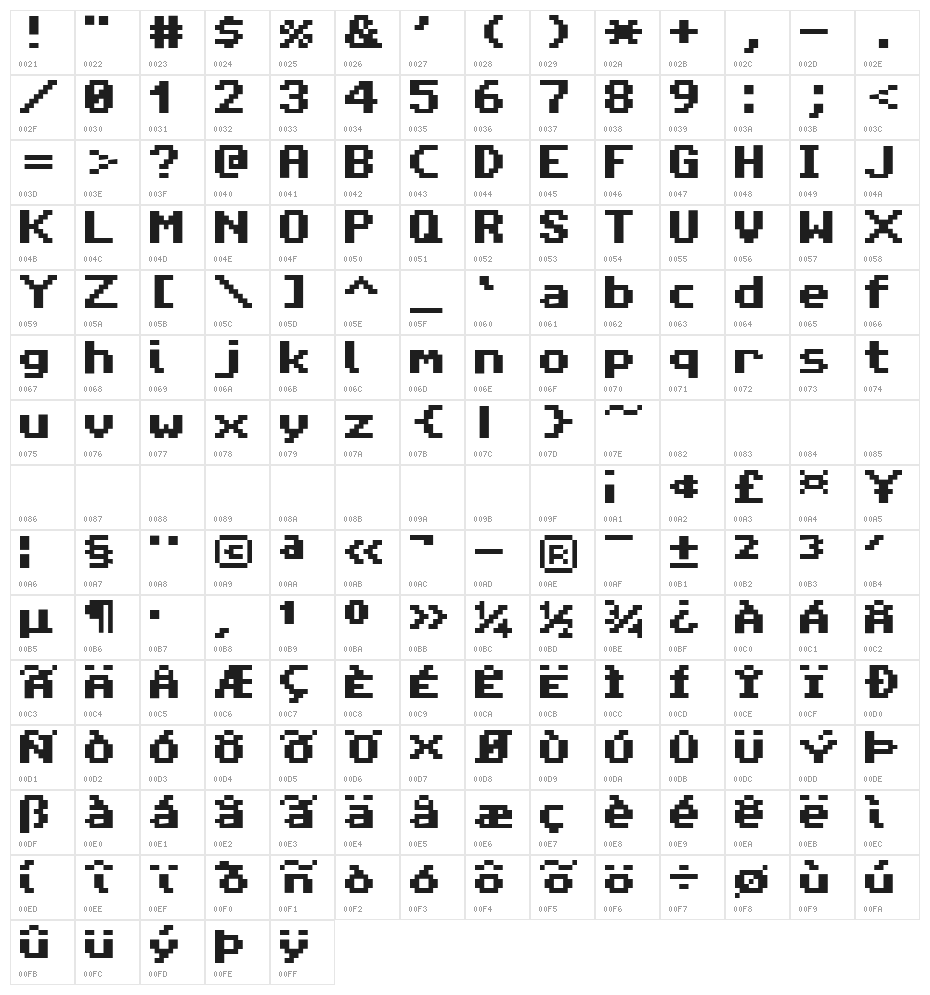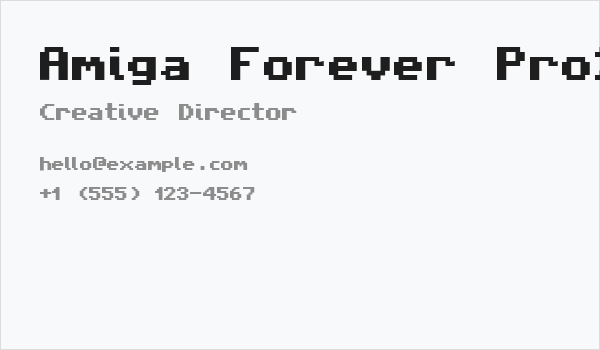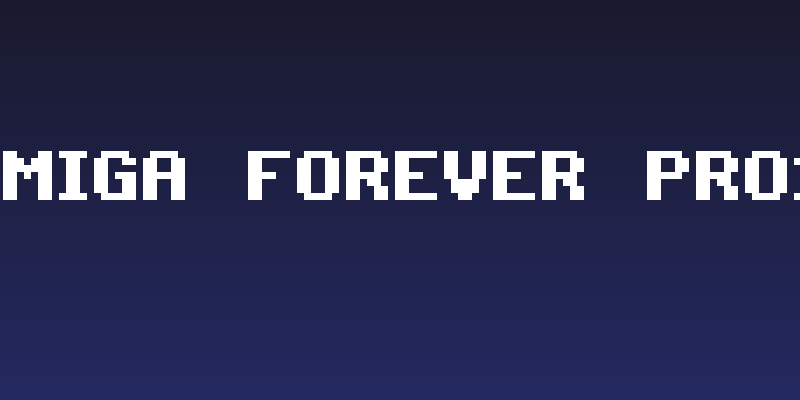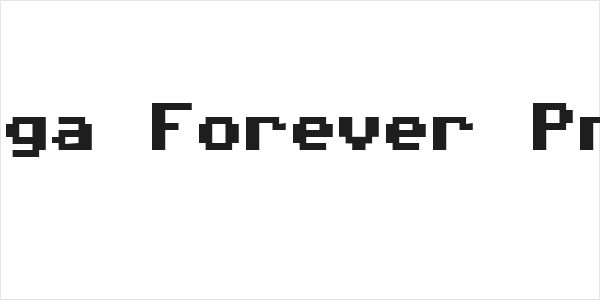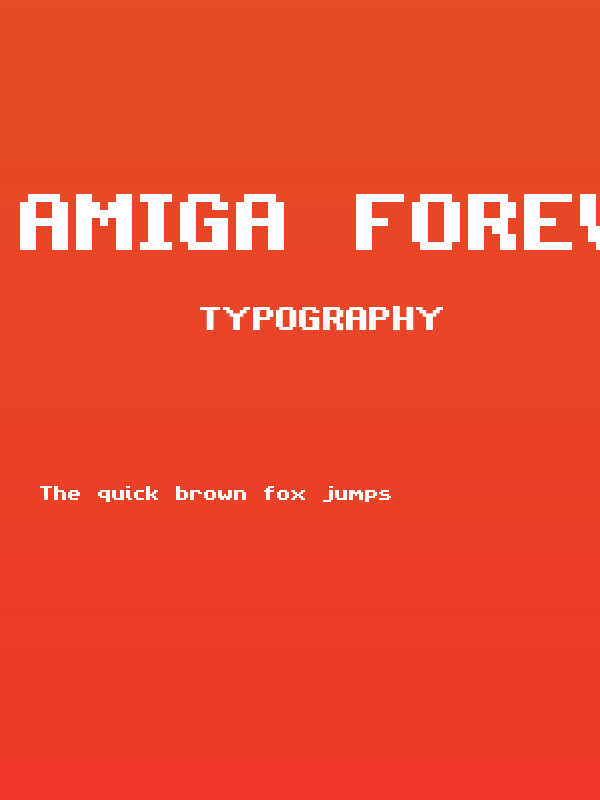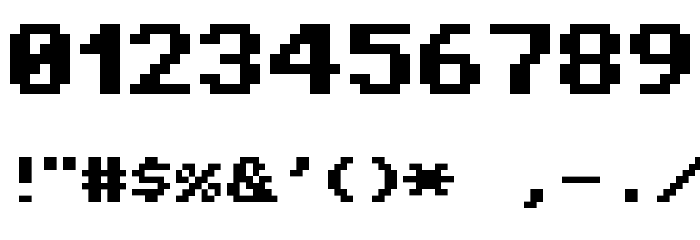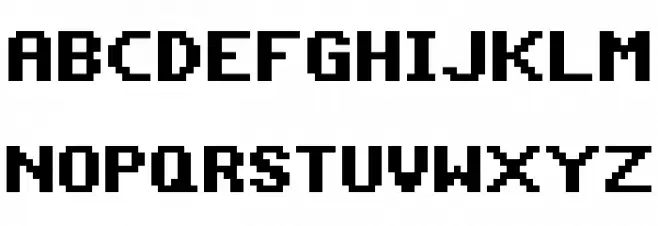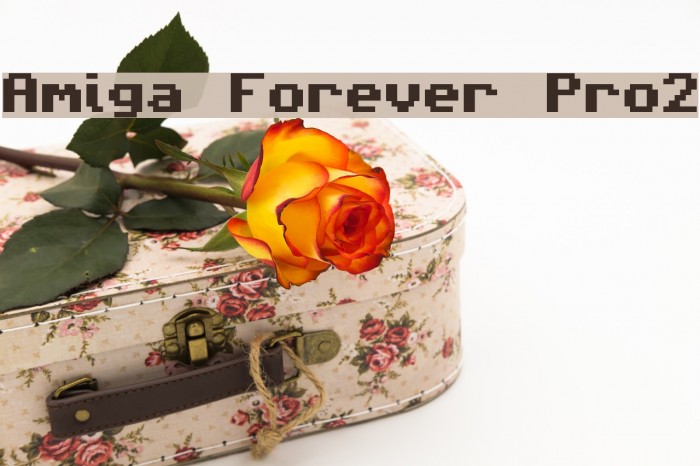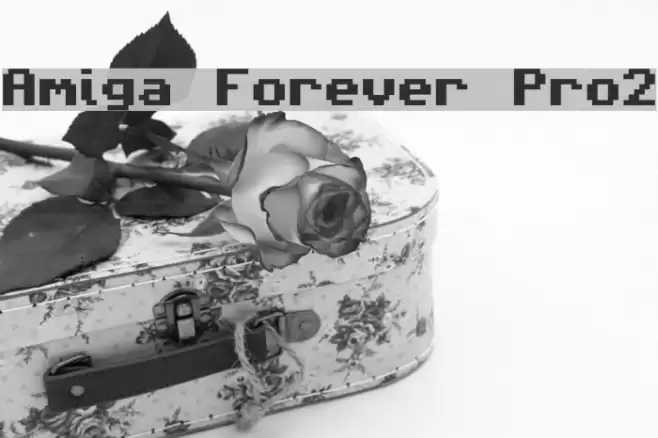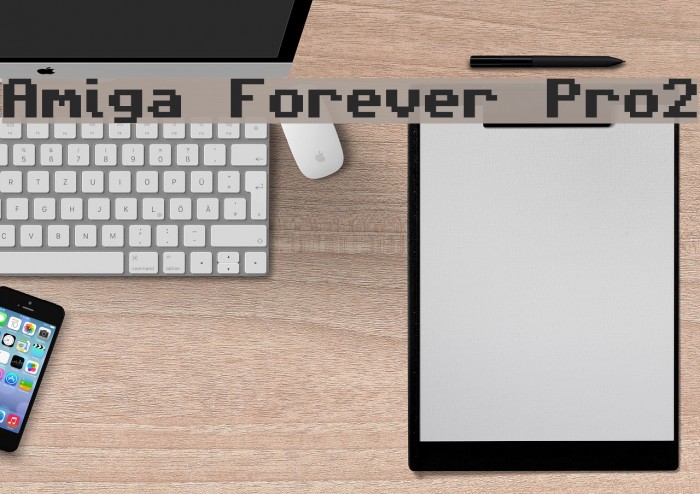
Amiga Forever Pro2 Font
| Категория | Pixel |
| Общий стиль | Vintage |
| Область применения | Logos, Headlines, Digital Art |
| Рекомендуемые проекты | Ideal for retro video games, digital art projects, nostalgic branding, and any design work that seeks to evoke a vintage digital feel. |